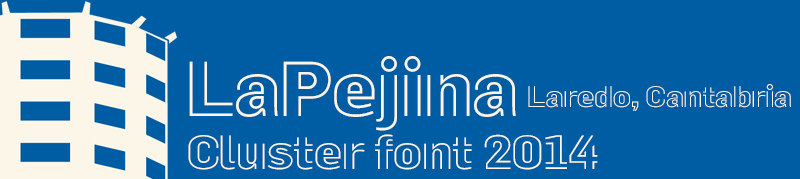
La Pejina font es mi primera tipografía continental, una sans serif de doble línea que homenajéa a Laredo en Cantabría y a toda la comarca pejina donde vivo y trabajo ahora. Cluster estratégico del Norte de España =========== The font is my first Pejina continental typography, a serif sans double line honors Laredo in Cantabria and the entire region pejina where I live and work now. Strategic Cluster of Northern Spain =========== • Regular & Italic • Descarga gratis las versión completa desde mi web. • Free download the full version in my website. • Números disponibles en mi web. • Numbers available on my website. • Only for personal use. Sólo para uso personal. • Licencia comercial disponible / Available commercial license.>> http://defharo.com/fonts/la-pejina-font/ |